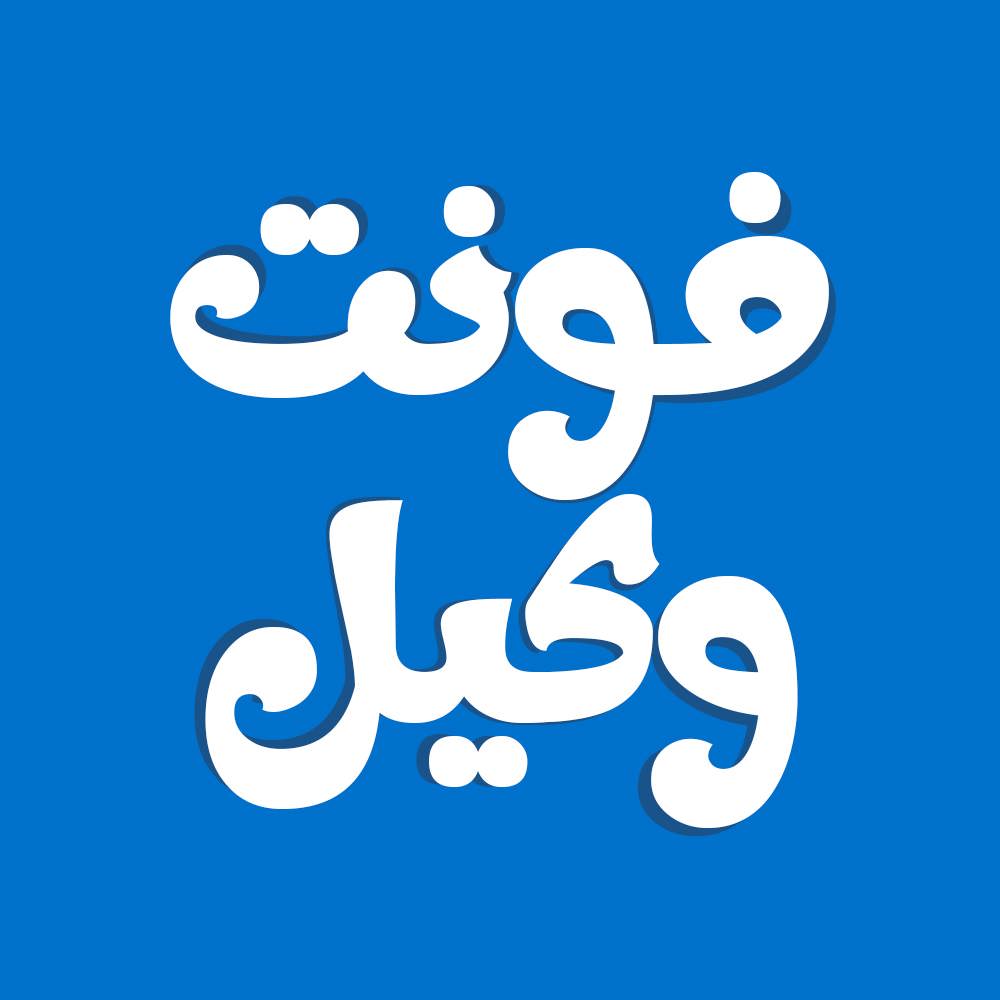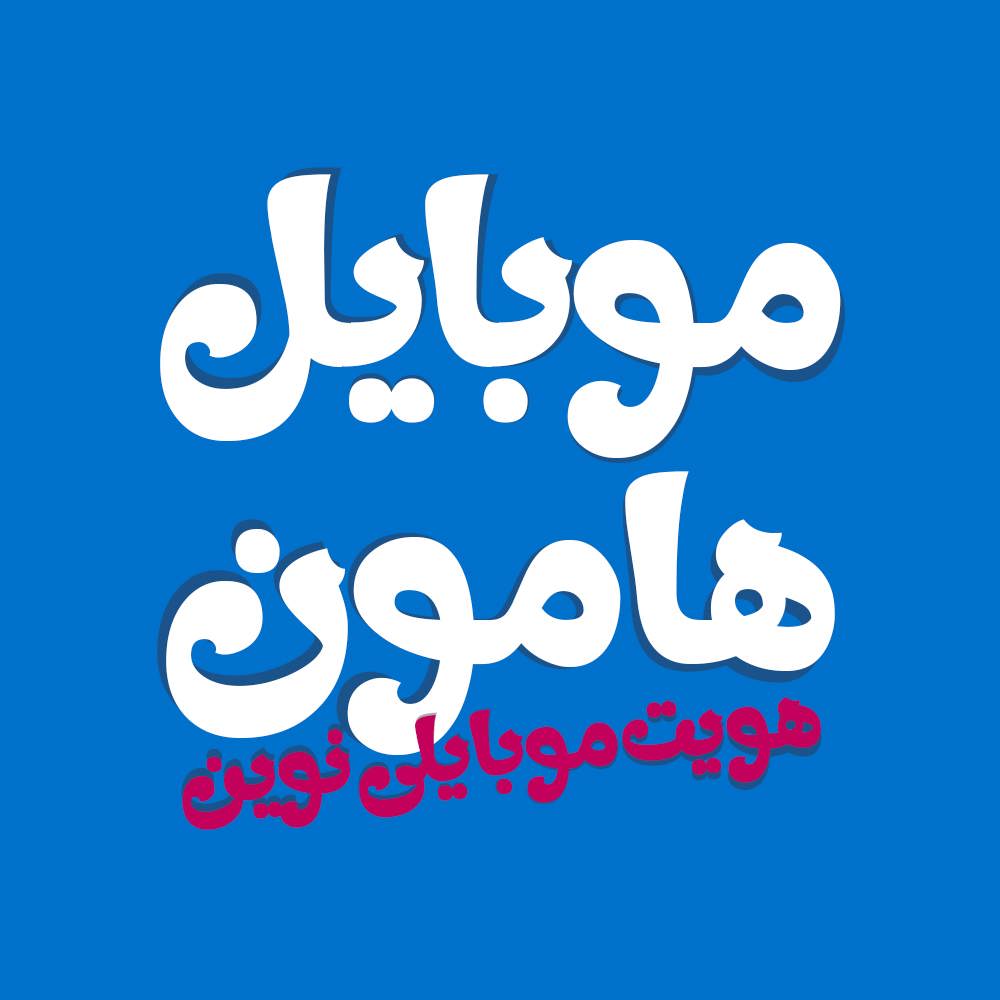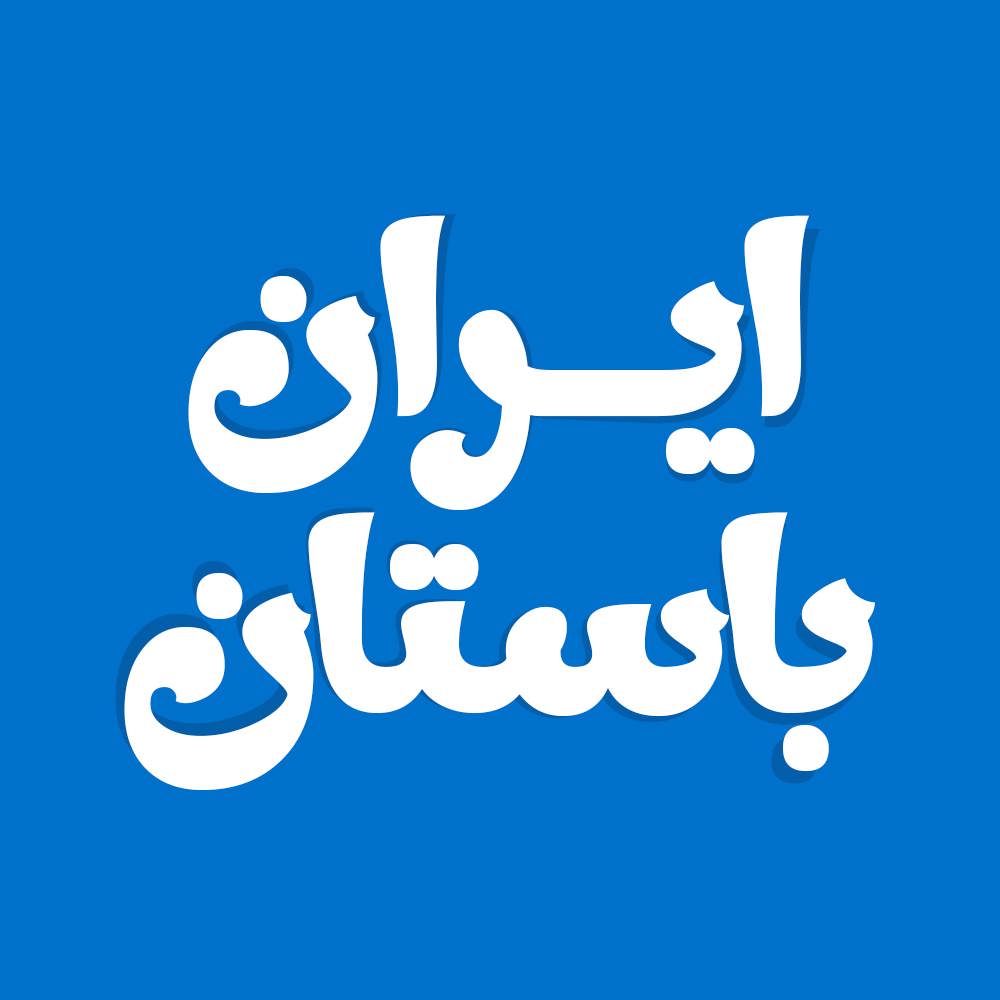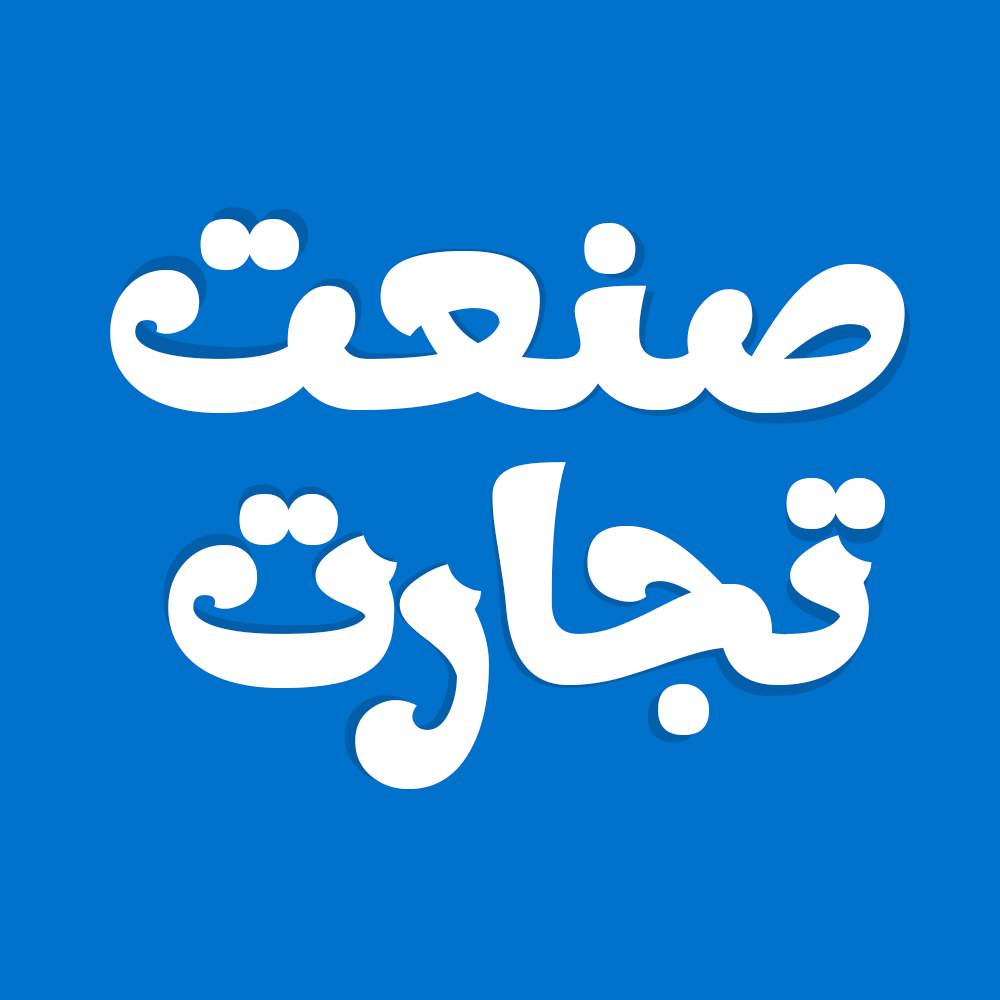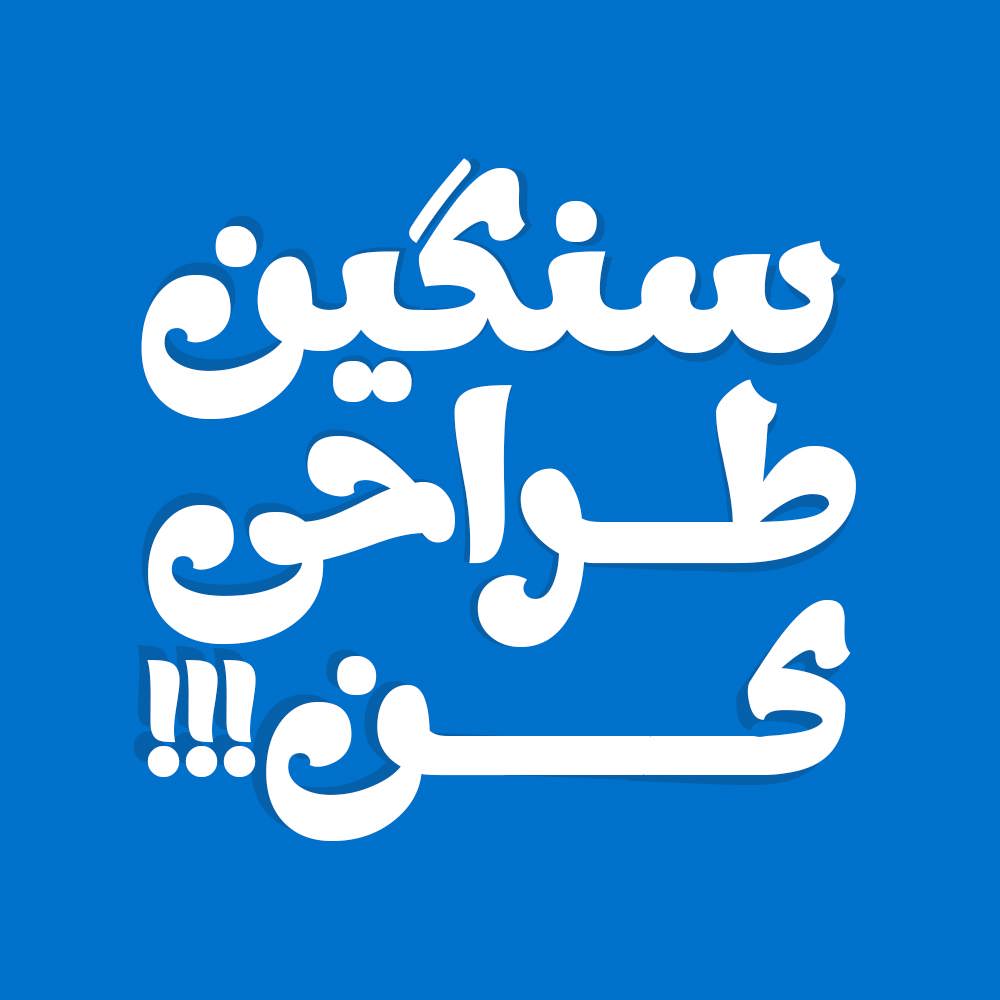
فونت فارسی وکیل Vakil Font
فونت فارسی وکیل دارای یک وزن سنگین می باشد و برای طراحی های مختلف همچون کتاب و تولید محتوای متن های کوتاه و بلند می باشد.…
فونت فارسی وکیل دارای یک وزن سنگین می باشد و برای طراحی های مختلف همچون کتاب و تولید محتوای متن های کوتاه و بلند می باشد. این فونت با ساختار حروف خود مناسب استفاده در تایپ های نوشتاری می باشد. فونت فارسی وکیل دارای حروف جایگزین و مناسب استفاده در عناوین و تیترها و جملات بلند و کوتاه و هم طراحی انواع تکست گرافی و استفاده در طراحی های خاص می باشد.
پیشنمایش و نمونه تایپ های فونت وکیل